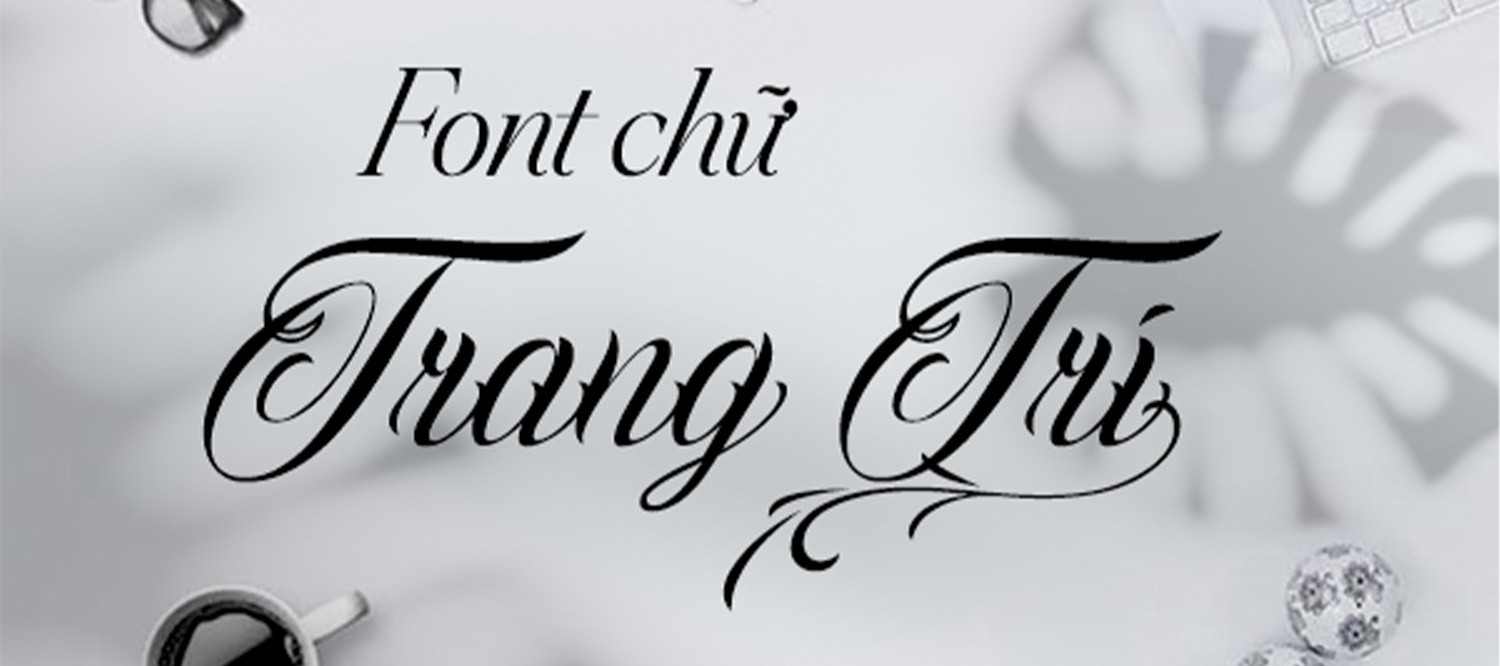
![[Tải Xuống] TOP 15 Font Chữ Trang Trí Việt Hoá Cho Thiết Kế 2025](https://cdn.s99.vn/blog/trangtri2.jpg)
Font chữ trang trí là những kiểu chữ có thiết kế độc đáo, thường được sử dụng để tạo điểm nhấn thị giác trong thiết kế như tiêu đề, logo, poster, thiệp cưới hoặc bìa sách. Không giống với các font chữ thông dụng như sans-serif hay serif, font trang trí thiên về biểu cảm, phong cách và cá tính. Với sự đa dạng trong thiết kế hiện nay, việc sử dụng font chữ trang trí được Việt hóa sẽ giúp các sản phẩm truyền tải thông điệp tốt hơn, tạo sự gần gũi với người dùng trong môi trường tiếng Việt.
Dễ thương, ngộ nghĩnh: thường dùng cho thiết kế cho trẻ em, sản phẩm vui nhộn
Mạnh mẽ, cá tính: áp dụng cho poster sự kiện, branding thể thao
Lãng mạn, mềm mại: phù hợp với thiệp cưới, spa, sản phẩm handmade
Cổ điển, vintage: dùng cho bao bì, nhãn mác, thiết kế retro
Thiết kế logo, nhận diện thương hiệu
Tiêu đề slide, infographics, báo cáo
Bìa sách, poster, banner sự kiện
Sản phẩm giáo dục, học liệu, in ấn sáng tạo
Serif trang trí
Display font (font tiêu đề)
Script / Handwritten
Decorative / Illustration font
1. TH Viettay 4 – Mảnh mai, tinh tế và thu hút
Font chữ viết tay Việt hóa với đường nét mảnh, mềm mại và uyển chuyển. TH Viettay 4 mang đến cảm giác nhẹ nhàng, bay bổng, phù hợp cho thiết kế thiệp cưới, sổ tay, hoặc typography nữ tính. Hỗ trợ tiếng Việt đầy đủ, dễ đọc và chuyên nghiệp.
2. TH Luxury 4 – Phông chữ serif sang trọng, cao cấp
Được thiết kế với dáng chữ thanh mảnh, TH Luxury 4 là font serif mang phong cách hiện đại pha cổ điển. Font thích hợp cho thiết kế thương hiệu cao cấp, thời trang, tạp chí hoặc hồ sơ năng lực doanh nghiệp. Việt hóa hoàn chỉnh, sử dụng mượt mà cho các dự án chuyên nghiệp.
3. TH Viettay 5 – Gần gũi, nhẹ nhàng và cảm xúc
Font viết tay với cấu trúc đơn giản, gọn gàng nhưng vẫn giữ được chất riêng trong từng nét. TH Viettay 5 phù hợp cho thiết kế blog, bài viết cá nhân, nhật ký, hoặc giáo án. Việt hóa đầy đủ, lý tưởng cho nội dung cảm xúc, thân thiện.
4. TH Romantic Heart – Lãng mạn với họa tiết trái tim mềm mại
Font chữ trang trí mang đậm cảm xúc với các nét trái tim xen kẽ trong thiết kế chữ. TH Romantic Heart là lựa chọn lý tưởng cho thiệp Valentine, sự kiện tình yêu hoặc thiết kế dành cho đối tượng trẻ trung, nữ tính. Việt hóa đẹp mắt, truyền tải được cảm xúc ngọt ngào.
5. TH Buttain Regular – Chữ nghiêng mềm mại, thanh lịch
TH Buttain là font script mang phong cách nghiêng nhẹ và tinh tế. Rất thích hợp để sử dụng cho tiêu đề, bao bì mỹ phẩm, hoặc các dự án thiết kế mang tính thủ công – cá nhân hóa. Font được Việt hóa chuẩn, dễ sử dụng và đọc tốt trên mọi nền tảng.
6. TH Viettay 2 – Đẳng cấp của nét viết tay thanh lịch
Mang phong thái sang trọng và tinh tế, TH Viettay 2 là sự lựa chọn hoàn hảo cho các thương hiệu cá nhân, mỹ phẩm, spa hoặc thiết kế có tính thẩm mỹ cao. Font được Việt hóa đầy đủ, hỗ trợ in ấn và kỹ thuật số.
7. TH Lusiana – Vui nhộn, hoạt hình và dễ thương
Font trang trí đậm chất hoạt hình, nét chữ mềm và tròn trịa. TH Lusiana rất lý tưởng cho thiết kế liên quan đến trẻ em, truyện tranh, lớp học mẫu giáo hoặc các sản phẩm sáng tạo. Việt hóa đầy đủ, dễ đọc và tạo cảm giác vui tươi.
8. TH Cartoon 7 – Mũm mĩm, tinh nghịch và đáng yêu
Font chữ hoạt hình với kiểu dáng bo tròn, phù hợp cho thiết kế sticker, nhãn dán, banner sinh nhật hoặc sản phẩm học liệu trẻ em. Việt hóa chuẩn, mang lại cảm giác thân thiện và vui vẻ cho người dùng.
9. TH Tan Meringue – Retro dễ thương pha cổ điển
Font trang trí lấy cảm hứng từ những poster retro cổ điển, nhưng được tinh chỉnh để trông hiện đại và trẻ trung hơn. TH Tan Meringue phù hợp với thiết kế bao bì, quán cà phê, poster, hoặc các sản phẩm mang nét vintage ngộ nghĩnh.
10. TH Hustle Culture – Cổ điển xen cá tính
Một trong những font mang phong cách cổ điển pha chút đường phố. Hustle Culture phù hợp với các thiết kế thương hiệu mạnh, áo thun, poster retro hoặc logo mang tính thời thượng. Font được Việt hóa đầy đủ và rõ ràng.
11. TH Holywest – Trang trọng, vintage và hoài cổ
TH Holywest là font serif cổ điển, với các đường nét cứng cáp và dày dặn. Đây là lựa chọn phù hợp cho poster phim, bìa sách, hoặc thiết kế hoài niệm mang tính truyền thống. Hỗ trợ tiếng Việt đầy đủ, dễ đọc.
12. TH Vintage 1 – Chất hoài niệm trong từng nét chữ
Font trang trí mang đậm tinh thần vintage với phong cách cổ điển, dày và đậm nét. TH Vintage 1 phù hợp với thiết kế banner retro, thương hiệu truyền thống, hoặc ấn phẩm mang màu sắc hoài cổ. Việt hóa tốt, dễ dùng.
Sử dụng font sai mục đích (ví dụ: dùng font cute cho hồ sơ công ty)
Tùy theo mục tiêu thiết kế, phong cách cá nhân và đối tượng người dùng mà bạn nên chọn font phù hợp. Danh sách 15 font ở trên sẽ giúp bạn tiết kiệm thời gian tìm kiếm, đồng thời thể hiện sự chuyên nghiệp trong từng dự án. Hãy tải xuống, thử nghiệm và sáng tạo – vì font chữ không chỉ là hình dạng ký tự, mà là ngôn ngữ của cảm xúc hình ảnh.